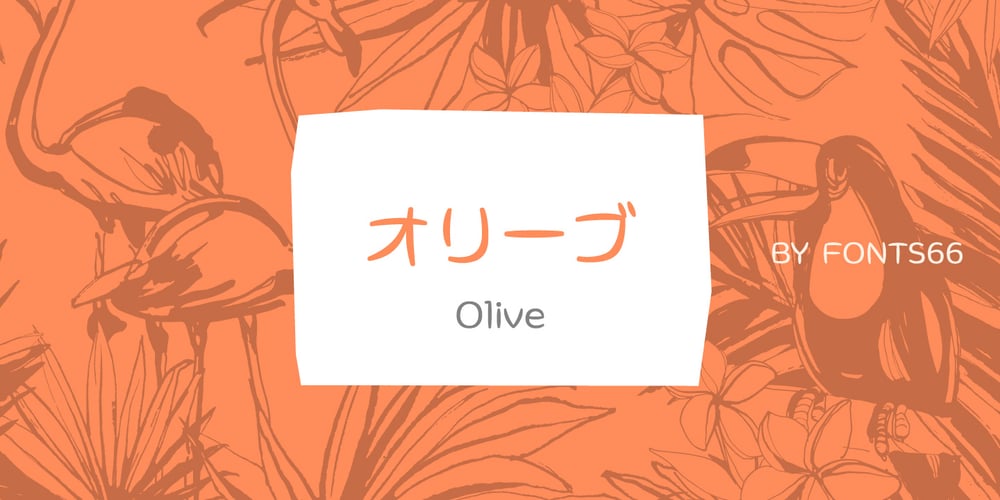
SF Olive
SF Olive font
SF Olive Font Family was designed by published by Fonts66. SF Olive contains 6 styles and family package options. The font for illustrations. Ideal for moving expressions. イラスト風味のフォントの発想から、形の単純な葉のイメージのエレメントを使い読む文字というより、楽しさを感じるフォントにしました。 写真やイラストカードに添えると柔らかな雰囲気がなじみ軽い雰囲気が得られます。 ダンスは風に吹かれたようなスウィングしているような文字です。